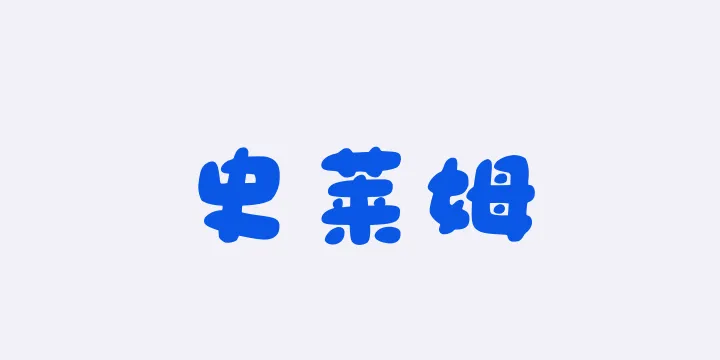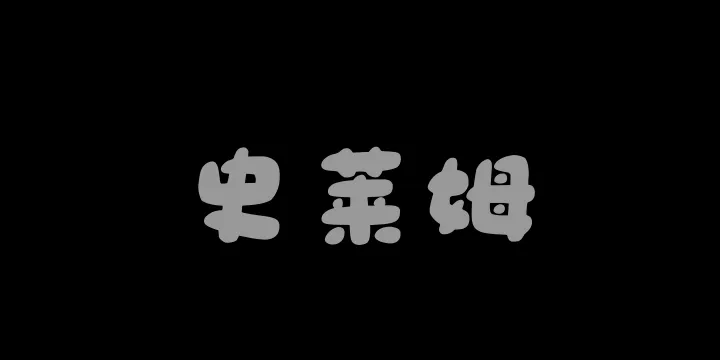
Aa史莱姆 By Aa字库 商用字体
字体全名: Aa史莱姆
字体简介: 这款字库采用全圆润笔画设计,横竖撇捺皆以饱满弧线收尾,彻底消解所有尖锐棱角。字形偏矮胖敦实,结构宽松舒展,点状笔画统一处理为圆润墨点,宛如鹅卵石般温润可爱。整体视觉萌趣治愈,亲和力极强,既保留汉字识别性,又充满软萌的卡通质感,适配亲子、美食、生活类品牌与童趣场景。